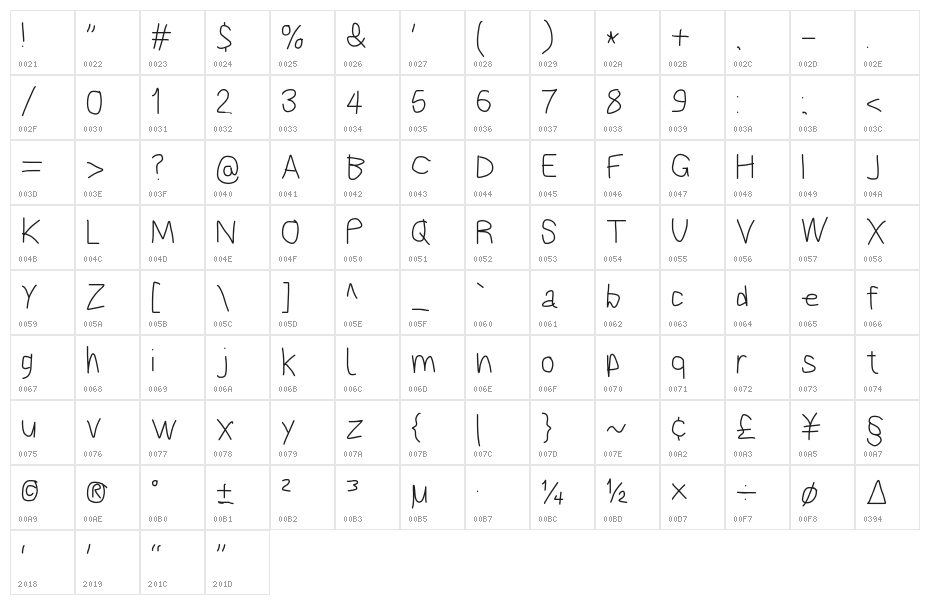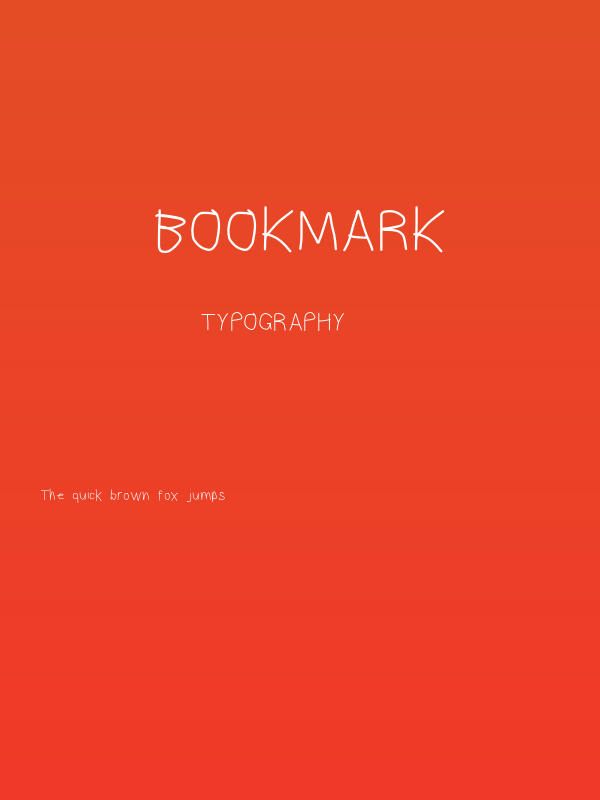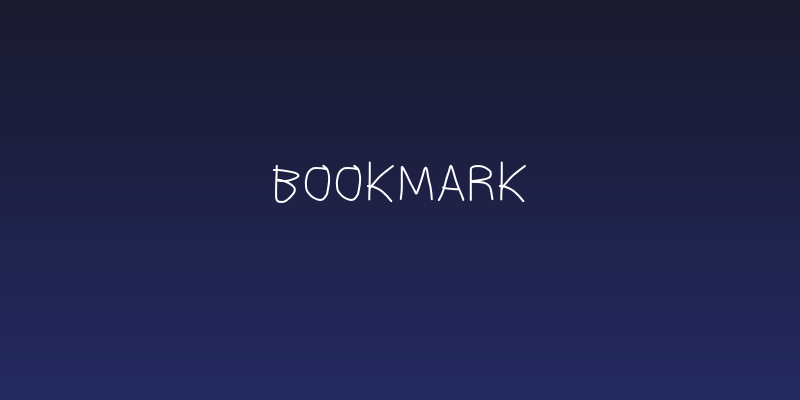
Bookmark Font
| Gesamtstil | Casual, Playful |
| Anwendungsfall | Headlines, Informal text, Creative projects |
| Vorgeschlagene Projekte | Ideal for greeting cards, children's books, personal blogs, and creative branding projects. |